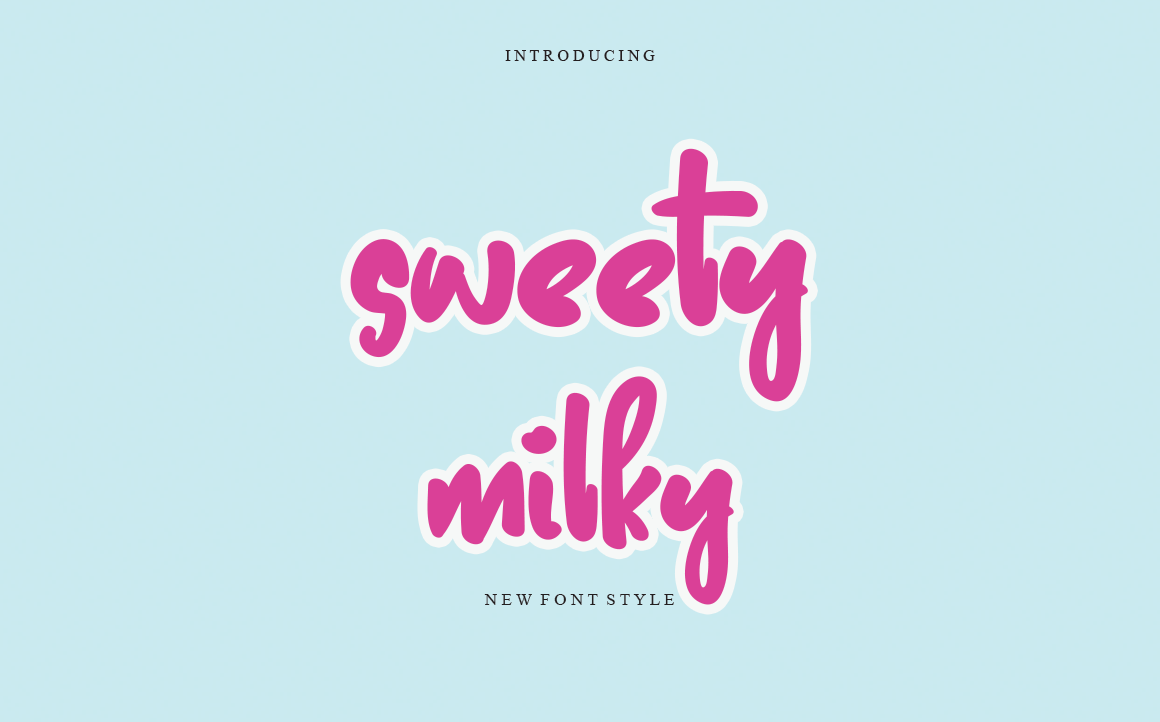
Sweety Milk Font – Download Grátis
A fonte ‘Sweety Milk Font’ é uma escolha perfeita para quem busca uma sensação leve e descontraída no seu design. Esta fonte levemente desenhada, com traços suaves e coloridos, é o ideal para tornar suas ideias criativas em verdadeiros trabalhos de arte. Se você está procurando um recurso para incorporar em sua próxima postagem do Instagram ou se encontra-se a precisar de uma fonte para seu próximo projeto de calligrafia DIY, ‘Sweety Milk Font’ certamente fará da sua criação algo único e divertido. Seja um desenho simplificado ou um texto estilizado, esta fonte consegue transmitir uma atmosfera descontraída e alegre que se adequa perfeitamente para qualquer projeto de design em tempo integral.